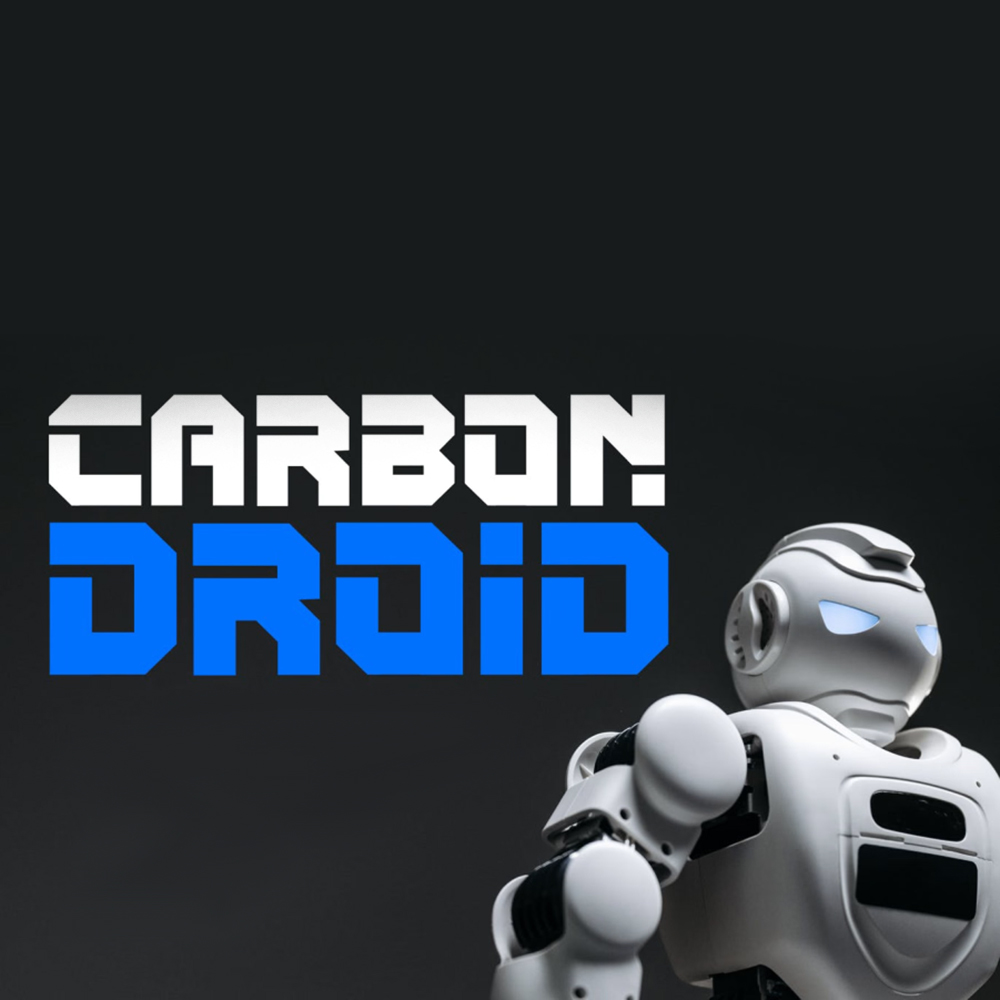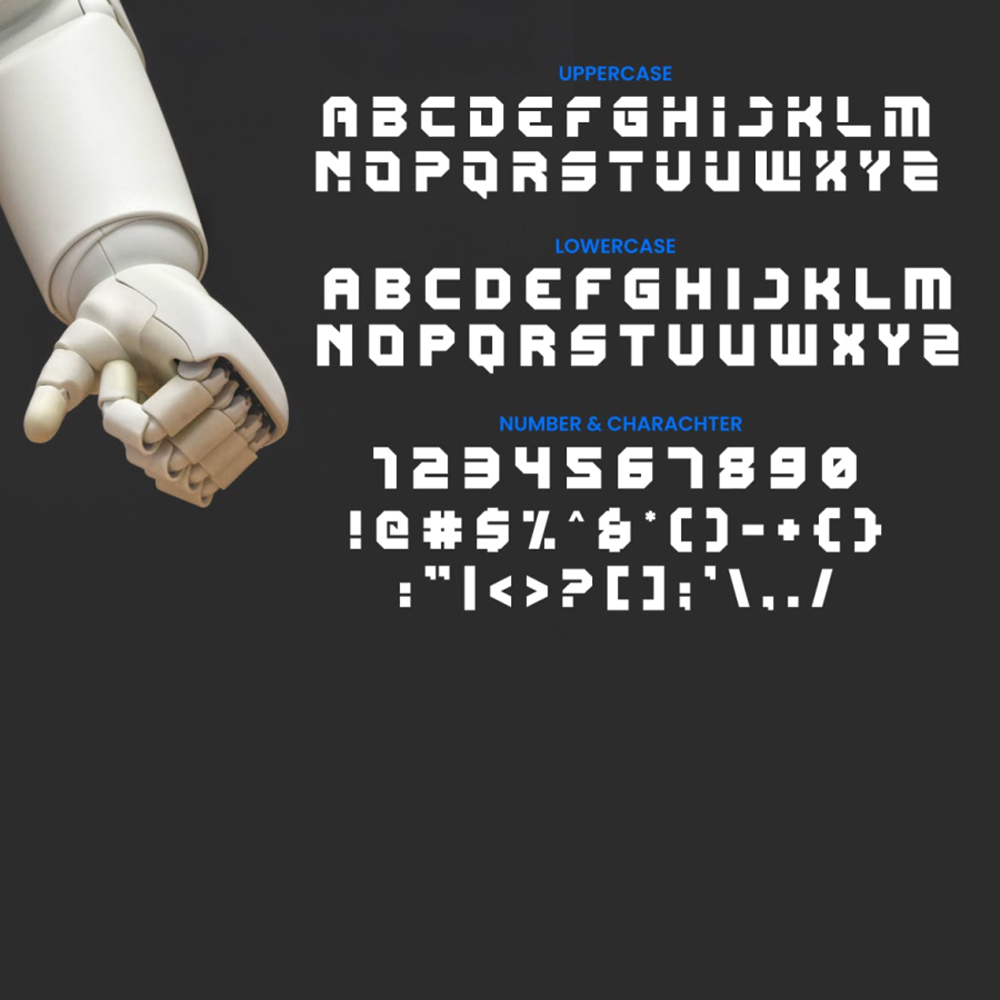
دانلود فونت انگلیسی Carbon Droid Font
فونت پرمیوم و انگلیسی Carbon Droid Font یک فونت مناسب برای مجلات، پوسترها، عناوین فیلمها، پوسترهای موسیقی، جلدهای یوتیوب، تصاویر کوچک یوتیوب، جلد صفحات رسانههای اجتماعی…
فونت پرمیوم و انگلیسی Carbon Droid Font یک فونت مناسب برای مجلات، پوسترها، عناوین فیلمها، پوسترهای موسیقی، جلدهای یوتیوب، تصاویر کوچک یوتیوب، جلد صفحات رسانههای اجتماعی و غیره با موضوع آینده و علم… عالی است.
مزایای استفاده از فونت لاتین Carbon Droid چیست؟